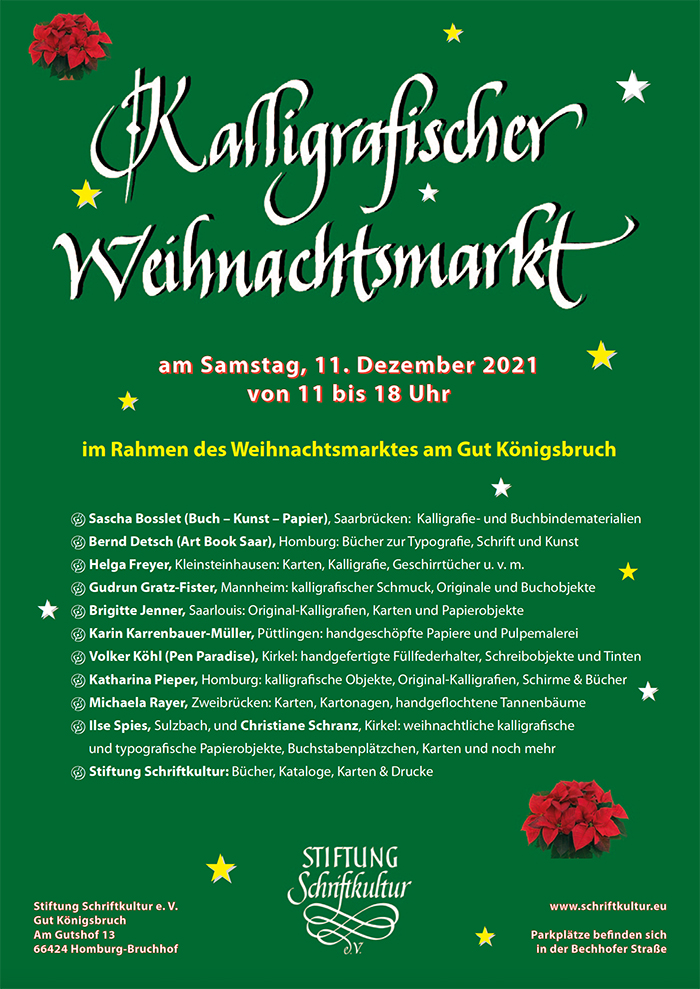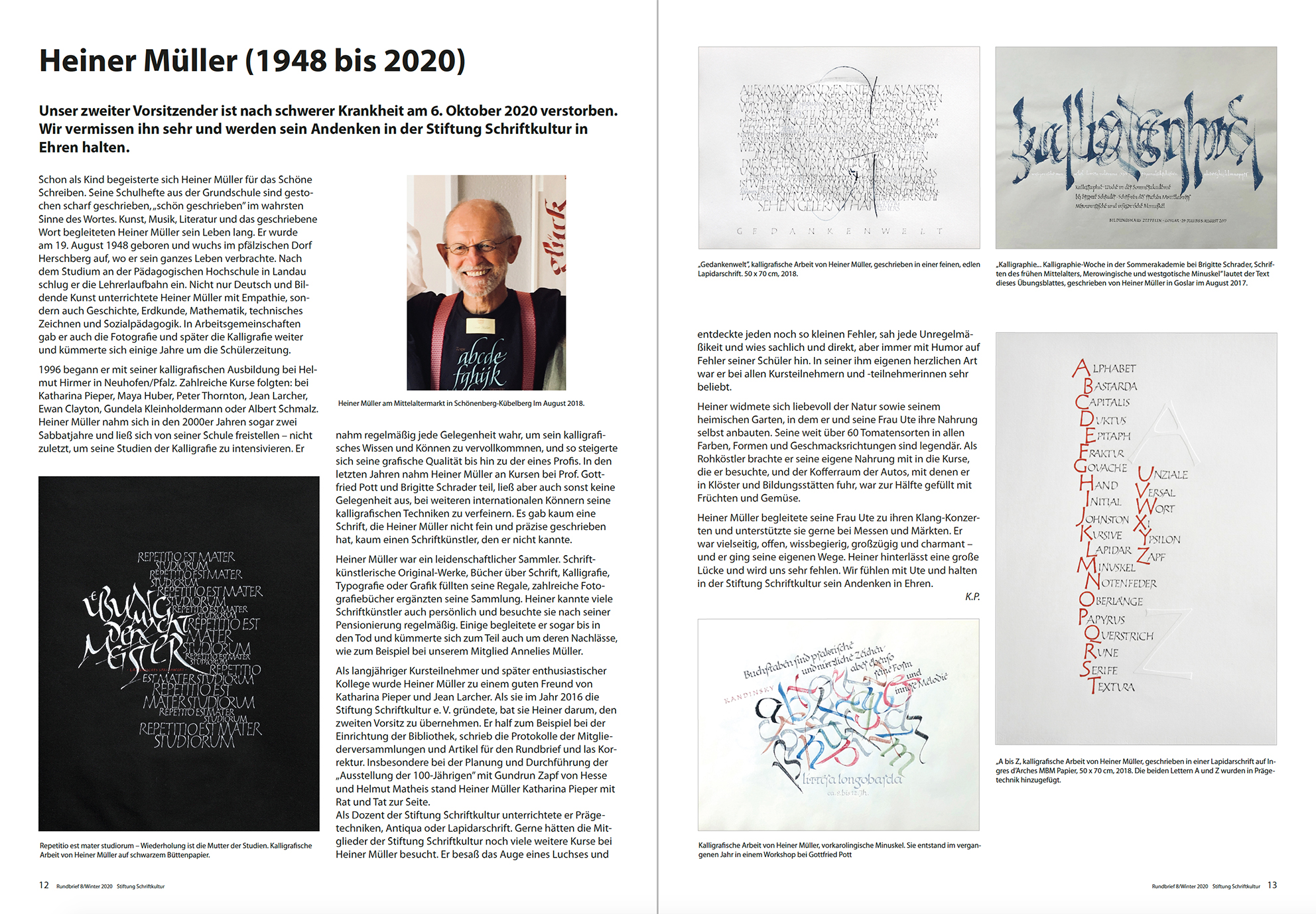
31.12.21 Unser Rundbrief Nr. 10, Winter 2021, ist soeben erschienen – alle Mitglieder haben ihn vor Weihnachten bekommen. Unsere Jahresgabe ist in diesem Jahr ein Katalog von Ayham Najjar, der bereits zum zweiten Mal in unserer Galerie seine Kalligrafien und Malereien ausgestellt hat. Trotz Corona und den damit verbundenen Einschränkungen war die Ausstellung gut besucht. Auch unser Weihnachtsmarkt am 11. Dezember klingt noch nach. Ein schönes Foto ist Françoise Mathis-Sandmaier an diesem Tag gelungen, sogar der zunehmende Mond lugte hinter den Wolken hervor. Lassen wir das Jahr 2021 hinter uns und begrüßen 2022 mit Mut, Ausdauer und einer guten Portion Selbstvertrauen! |
14.12.21 Am Samstag, den 11. Dezember, fand auf dem gesamten Gut Königsbruch der Weihnachtsmarkt statt. Möglich war dies durch alle erdenklichen Vorsichtsmaßnahmen seitens der Besitzer: Eine Teststation vor Ort, Eingangskontrollen, Maskenpflicht. Die Mitglieder der Stiftung Schriftkultur, die Aussteller, die Besucher und Katharina Pieper freuten sich, dass der kalligrafische Weihnachtsmarkt in unseren Räumen gut besucht wurde. Es konnten in weihnachtlicher Stimmung viele Gespräche geführt, Freundschaften gefestigt und Kreativ-Kalligrafisch-Künstlerisches erworben werden. Im Hof sorgten neben dem Weihnachtsbaumverkauf die Jäger mit Wildspezialitäten und Glühwein für das leibliche Wohl, in der Veranstaltungshalle gab es Kunsthandwerk, Honig, Schmuck und Plätzchen, und gegen Abend kam der Nikolaus mit einem weißen Pferd und beschenkte die Kinder. Wir werden uns an diesen speziellen Tag erinnern! |
19.11.21 Am vergangenen Mittwoch hielt die Kunsthistorikerin Dr. Jutta Schwan einen interessanten und kurzweiligen Vortrag zum Thema "Bilder, Ranken und Elefantenrüssel – die bunte Welt der Initialen". Zum ersten Mal konnten nicht nur die in Präsenz anwesenden Zuhörer dem Vortrag lauschen, sondern auch weitere Mitglieder, die sich online zu uns schalten konnten – eine Premiere und ein Einstieg in eine neue Zeit! Auf diese Weise war es möglich, über den Computerbildschirm von zu Hause aus am Vortrag teilzunehmen. Sascha Boßlet, unser Administrator und Host, ließ die Angemeldeten virtuell "eintreten", und so waren auch Mitglieder aus dem Schwäbischen und Badischen, aus Mannheim oder auch direkt aus Homburg bei uns. Es gibt noch das ein oder andere technische Problem zu verbessern, doch dies war schon mal ein Anfang. Frau Dr. Schwan zeigte in ihren Bildbeispielen Initialen aus Büchern der Bibliotheca Bipontina in Zweibrücken, die auf dem Nachlass des Pfalzgrafen Karl I. von Pfalz-Birkenfeld (1560 bis 1600) beruht und wahre Schätze der Buchkunst aufbewahrt. Eine bemerkenswerte Ausstellung im Jahr 2018 befasste sich mit diesen Büchern und deren Initialen. Nach dem Vortrag konnten sich die Anwesenden eine kleine Präsentation mit handgeschriebenen und gezeichneten Initialen ansehen. Herzlichen Dank, Frau Dr. Schwan! Der Vortrag wurde von uns aufgezeichnet – bei Interesse bitte bei uns melden. |
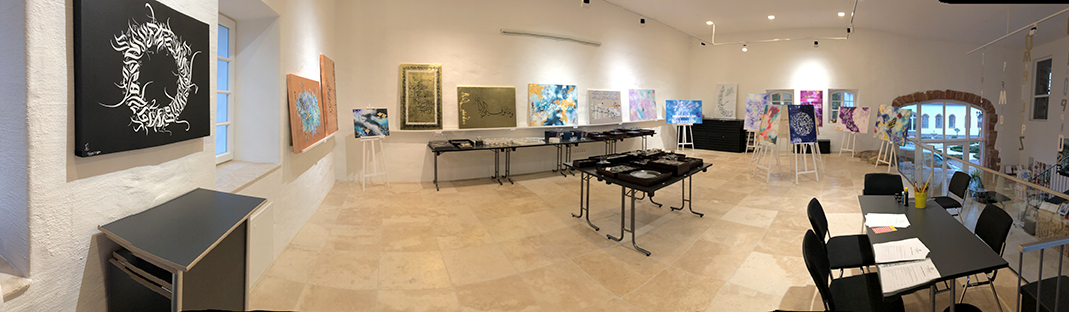
Panoramafoto derGalerie mit der Ausstellung von Ayham Najjar
15.11.21 Die Ausstellung "Orientalische Kalligrafie & Malerei"von Ayham Najjar ist gestern zu Ende gegangen. Sie wurde mit einer Finissage beendet, die um 11 Uhr begann. Bis 18 Uhr kamen die Besucher, coronabedingt weniger als zu "normalen" Zeiten. Katharina Pieper begrüßte zu Beginn die Besucher und führte in das Werk von Ayham ein. Anschließend bedankte sich Ayham in fehlerlosem Deutsch und stand für Gespräche zur Verfügung. Kleine Leckereien, ein Gläschen Cremant und feines Gebäck rundeten den Finissage-Tag ab. Die Rede von Katharina Pieper kann hier nachgelesen werden: REDE. Ayham Najjars Bachelorarbeit, der Entwurf für ein fiktives Kalligrafiemuseum in Aleppo, kann hier über YouTube angesehen werden: https://www.youtube.com/watch?v=a4JudbRc_Hg |
01.11.21 Die Ausstellung "Orientalische Kalligrafie & Malerei" ist eingerichtet und wurde gestern, am 31. Oktober, zu ersten Mal der Öffentlichkeit gezeigt. Zahlreiche Besucher kamen am Nachmittag, um die Ausstellung anzusehen. Nicht nur die Werke auf Holz und Leinwand, sondern auch die wunderschönen Glasobjekte und Gebrauchsgegenstände fanden eine große Resonanz. Die Ausstellung kann noch am 7. und am 14. November von 15 bis 18 Uhr angesehen werden.Zum Abschluss des Tagen gab Ayham eine kleine Privatstunde in arabischer Kalligrafie für eine Designstudentin aus Karlsruhe. |
26.10.21 Am Wochenende veranstalteten wir den Kurs "Cancellaresca" unter der Leitung von Katharina Pieper. Unsere Bibliothek wurde wieder einmal zum Scriptorium, in dem die klassische italienische Kursive nach historischen Vorbildern nachgeschrieben wurde. Schwungvolle Klein- und Großbuchstaben sowie lateinische Texte, z. B. der bekannte Text aus dem 8. Jahrhundert "O quam gravis est scriptura... (O wie schwer ist das Schreiben...) begleiteten die Teilnehmerinnen. Eine Teilnehmerin reiste aus Bayern an, eine andere ist gerade auf "Heimaturlaub" in der Pfalz, lebt aber in Brasilien. _ Rechts: Der Weihnachtsmarkt, der in diesem Jahr wieder stattfinden darf, wirft seine Schatten voraus. Es wird bereits eifrig geschrieben, gefalzt und vorbereitet, wie hier an zwei Beispielen von selbst gestalteten Karten von Michaela Rayer und Ilse Spies zu sehen ist. Der Markt wird am Samstag, den 11. Dezember stattfinden. |
12.10.21 Der Abendkurs zum Thema "Unziale" mit Michaela Rayer hat begonnen. Michaelas gute Vorbereitung erspart den Teilnehmerinnen zum Beispiel das am Anfang aufwendige Linien Ziehen. Nun muss noch viel geübt werden! Gestern, am 2. Abend, kam unser Mitglied Volker Köhl (Pen Paradise) zu Besuch und stellte seine neue Collection Federhalter vor. Wunderbare und sehr edel gefertigte Halter aus gefärbtem Acryl und verschiedenen Hölzern liegen gut in der Hand und sind ein Schmuckstück für jeden Kalligrafie-Begeisterten. Wer möchte, kann sich hier schon mal einen Eindruck des Sortiments an Federhaltern, Füllern und Tinten machen. Demnächst gibt's bei uns auch wieder neue Tinten aus Volker Köhls Sortiment. https://www.pen-paradise.de/Impressum |
27.09.21 Am 24. September veranstaltete die Stiftung Schriftkultur ihre diesjährige Mitgliederversammlung, nach einem Jahr coronabedingter Abstinenz. Auf der Tagesordnung standen unter anderem die Wahl des neuen 2. Vorsitzenden als Nachfolger von Heiner Müller. Sascha Boßlet aus Saarbrücken, wiss. Mitarbeiter im Deutschen Zeitungsmuseum Wadgassen, Inhaber eines Geschäfts für Buchbinde- und Kalligrafiematerialien und erfahrener Kursleiter, wurde einstimmig gewählt. Herzlich willkommen und auf eine gute Zusammenarbeit! – Am vergangenen Sonntag, dem 26. September, fand, ebenfalls nach langer Pause, die erste größere Veranstaltung als Tag der offenen Tür statt. Viele Mitglieder, Besucher, Freunde und Kollegen nutzten die Gelegenheit, sich mit Gleichgesinnten zu treffen und sich auszutauschen. Endlich waren die Räume der Stiftung Schriftkultur mal wieder so richtig belebt! |
| 20.09.21 Soeben ging ein neuer Wochenend-Kurs zum Thema "Handlettering – Schrift schreiben und zeichnen" unter der Leitung von Katharina Pieper zu Ende. Bei strahlendem Sonnenschein fanden sich sechs Teilnehmerinnen ein, die ins Schreiben mit Pinselmarkern, Lettering-Pens und Finelinern eingeführt wurden und viel Neues und Kreatives lernten. Lettering als Bindeglied zwischen Handschrift und Kalligrafie gibt unendliche Möglichkeiten der Formvariation, Farbgestaltung oder durch Zufügen von Schatten, Mustern und Zeichnungen zusätzliche Dekore. |
| 06.09.21 Am vergangenen Wochenende konnte endlich wieder ein Kurs in der Galerie der Stiftung Schriftkultur stattfinden – der erste Kurs im Herbstprogramm 2021. Sascha Boßlet, wissenschaftlicher Mitarbeiter im Deutschen Zeitungsmuseum und Fachmann um alle Themen rund um Papier, Buch und Druck, leitete einen Kurs zum Thema "Buchbinden und freie Heftung". In nur zwei Tagen gab er viel Wissen und handwerkliches Können an die Teilnehmer weiter, die nicht nur von Herrn Boßlets enormem Sachverstand profitieren, sondern auch in zahlreichen außergewöhnlichen Papieren aus Nepal, Mexiko, Italien oder Japan schwelgen durften. Zum Einsatz als Bucheinband kamen neben Papieren auch Leder, Filz, Bast, Holz und Naturmaterialien. Ein "Powerkurs" für alle Teilnehmenden, die nicht nur viel lernten, sondern auch zahlreiche schöne Buchobjekte in japanischer Fadenheftung und weiteren Bindetechniken gestalteten. |
der zukünftigen Schriftgrafikerinnen. Eine schöne Zeit mit vielen Fragen, Antworten und intensiven Fachgesprächen!
31.7.2018 Inzwischen durften wir diverse Sachspenden entgegennehmen, z. B. mehrere Bände von Facsimile-Drucken aus der "Galerie der schönsten Bücher"
des Facsimile Verlag Luzern.Hier sieht man die Incipitseite des Markusevangeliums aus dem Book of Lindisfarne (Lindisfarne Gospel). Paul Spitzer aus Niederaichbach